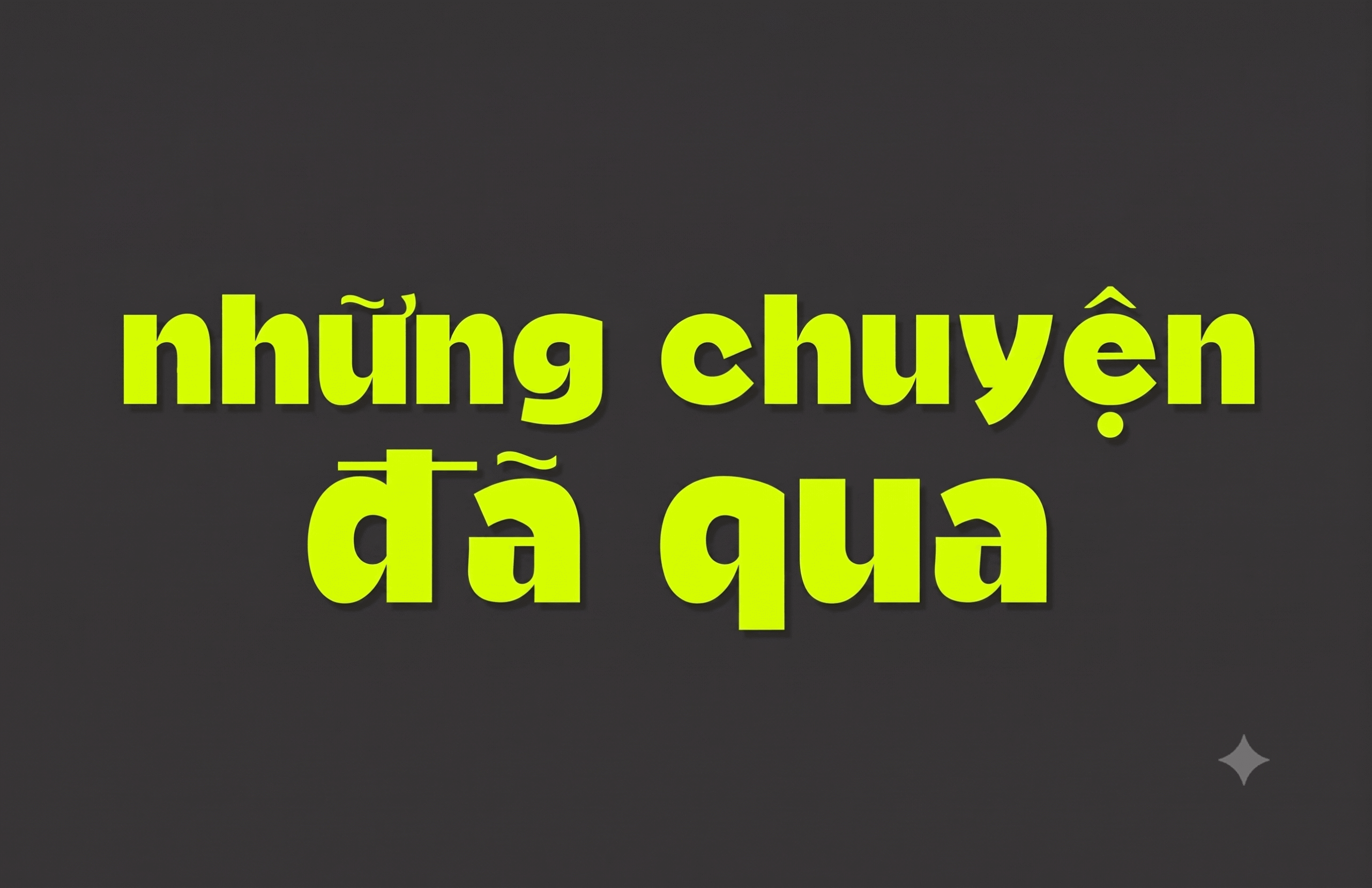
Font Việt Hóa 1FTV VIP Bakery Cafes: Giải Pháp Thiết Kế Hoàn Hảo Cho Quán Cafe & Tiệm Bánh
Bạn đang tìm kiếm một phông chữ độc đáo, ngọt ngào và chuyên nghiệp để xây dựng hình ảnh cho thương hiệu F&B của mình? Font Việt hóa 1FTV VIP Bakery Cafes chính là mảnh ghép bạn đang thiếu. Đây là bộ phông chữ cao cấp được thiết kế đặc biệt, mang đến hơi thở nghệ thuật và sự tinh tế cho các tiệm bánh, quán cà phê hay nhà hàng.
Giới Thiệu Về Font 1FTV VIP Bakery Cafes
Trong ngành dịch vụ ăn uống (F&B), yếu tố thị giác đóng vai trò cực kỳ quan trọng để thu hút thực khách. Một phông chữ đẹp không chỉ truyền tải thông tin mà còn định hình cá tính thương hiệu. Font 1FTV VIP Bakery Cafes đã được Việt hóa chỉn chu, giúp các nhà thiết kế dễ dàng thao tác với văn bản tiếng Việt mà không lo lỗi hiển thị dấu, đồng thời giữ trọn vẹn nét thanh lịch của bản gốc.
Những Ưu Điểm Nổi Bật Của Bộ Font
Tại sao bộ phông chữ này lại được giới thiết kế ưa chuộng đến vậy?
• Việt hóa chuẩn xác: Hỗ trợ đầy đủ bảng mã Unicode tiếng Việt, các dấu câu được tinh chỉnh tỉ mỉ, hài hòa và đồng nhất với từng ký tự.
• Phong cách đặc trưng: Mang hơi hướng thủ công (hand-crafted), pha trộn hoàn hảo giữa sự ngọt ngào của những chiếc bánh ngọt và nét thư giãn, ấm cúng của không gian quán cà phê.
• Đường nét tinh tế: Sự kết hợp giữa các nét thanh, nét đậm được xử lý mượt mà, tạo cảm giác gần gũi nhưng vẫn toát lên vẻ cao cấp (VIP).
Ứng Dụng Hoàn Hảo Trong Thiết Kế F&B
Với tính linh hoạt cao, bộ font này có thể tỏa sáng trong rất nhiều hạng mục thiết kế của quán:
• Thiết kế Logo & Bộ nhận diện: Tạo ra điểm nhấn thương hiệu mạnh mẽ, dễ nhớ và mang đậm phong cách riêng.
• Thiết kế Thực đơn (Menu): Biến những dòng tên món ăn, thức uống trở nên hấp dẫn và kích thích vị giác hơn.
• Bao bì sản phẩm: Nâng tầm giá trị thẩm mỹ cho hộp đựng bánh, túi giấy hay ly cafe take-away.
• Truyền thông Mạng xã hội: Làm nổi bật các chương trình khuyến mãi trên banner, bài đăng Facebook, Instagram.
Tổng Kết
Việc đầu tư vào kiểu chữ chính là đầu tư trực tiếp vào hình ảnh thương hiệu. Font Việt hóa 1FTV VIP Bakery Cafes chắc chắn sẽ là “trợ thủ đắc lực” giúp không gian F&B của bạn ghi điểm tuyệt đối trong mắt khách hàng. Hãy tải xuống và trải nghiệm ngay sự khác biệt mà bộ font này mang lại!